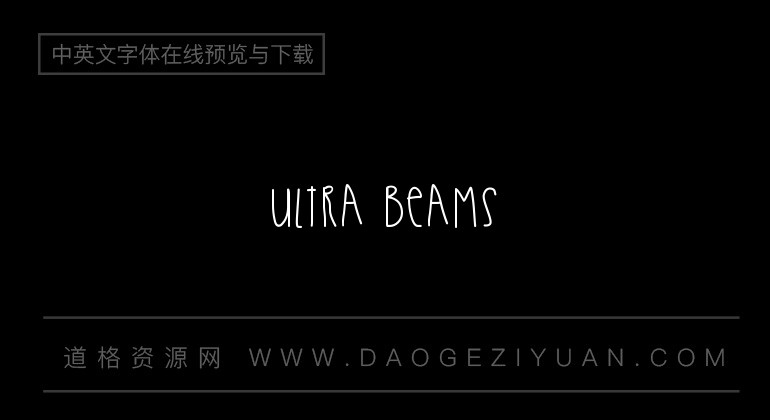
Ultra Beams是一种现代风格的sans-serif字体。它由设计师Juri Zaech创建,旨在为设计师和创意人士提供一种独特的字体选择,可以在各种项目中使用。 Ultra Beams字体具有极简主义的外观和突出的线条,这使它在设计中具有很高的可读性和视觉冲击力。它的字母形状非常独特,包括像“S”和“Z”这样的字母,它们的形状非常流畅,同时保留了字体的现代和未来感。 Ultra Beams包括两种字重:Regular和Bold,并支持多种语言和字符集。它适用于许多不同类型的设计项目,特别是关于科技、创新、未来和现代主义的主题。 总之,如果你需要一种现代和独特的字体来增强你的设计效果,那么Ultra Beams是一个不错的选择。内容介绍
Ultra Beams是一款非常不错的手写艺术字体,具有很好的视觉感,适合于文化类的宣传设计、商业类品牌的广告和产品包装设计以及个性化文字排版等较多场景。